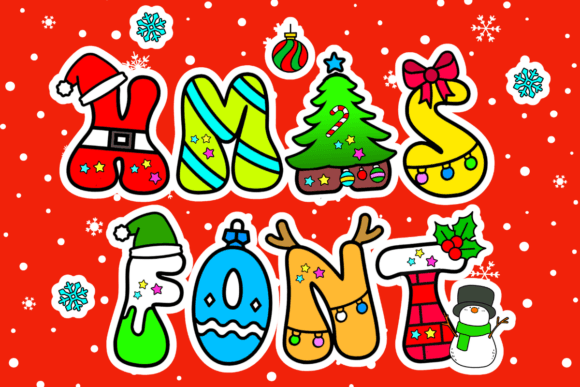
Xmas Doodle
Якщо ви шукаєте високоякісні ресурси, такі як Xmas Doodle, цей преміум-пакет є фантастичним вибором для ваших творчих проектів.
Створений з високою точністю, Xmas Doodle забезпечує чисті вектори, плавну типографіку та комерційну ліцензію для вашого спокою.
Незалежно від того, чи створюєте ви продукти POD (друк на вимогу), весільні запрошення або графіку для соціальних мереж, Xmas Doodle стане ідеальним вибором.